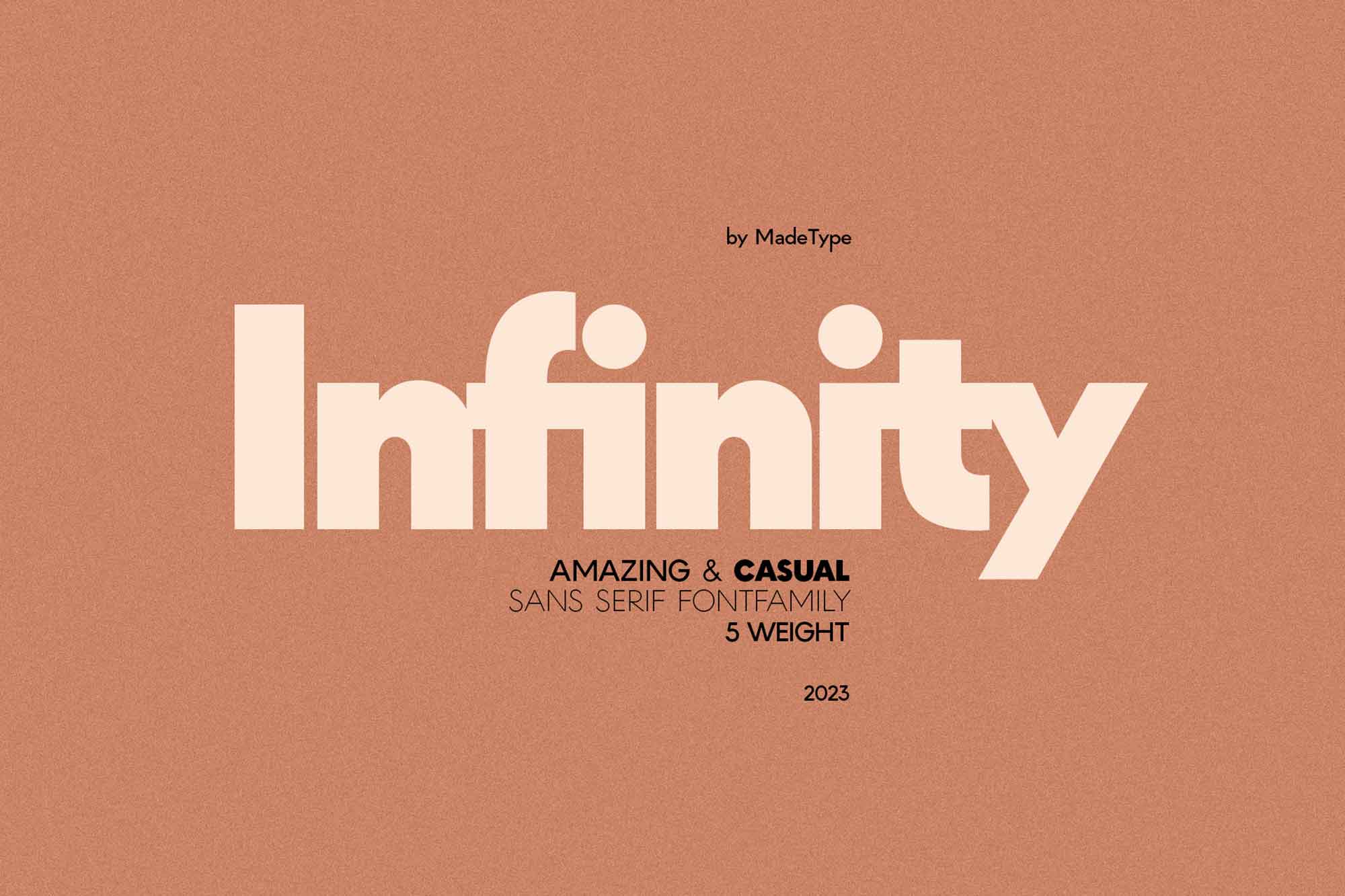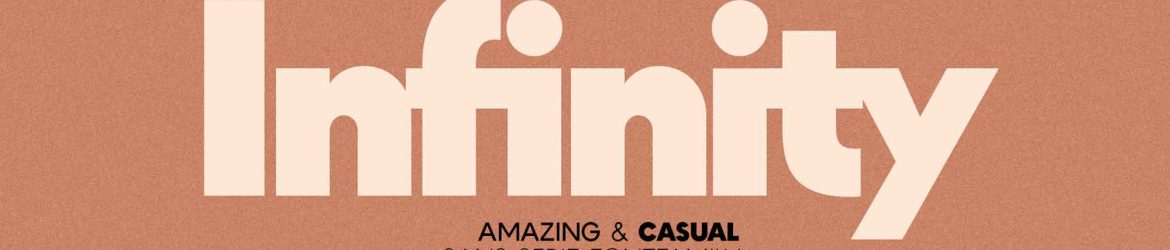
Made Infinity Font – Download Grátis
A Made Infinity é uma família de fontes sans-serif que compreende cinco pesos: fino, leve, regular e grosso. Suas linhas elegantes e elegantes fazem deste um recurso fonte perfeito para projetos que exigem uma mistura de simplicidade e versatilidade. O resultado é um design que é tanto amigável quanto versátil. A Made Infinity é uma ótima escolha para os designers gráficos que buscam uma fonte que seja elegante e versátil. Suas linhas delicadas e geométricas são perfeitas para aplicações em posters, capas de livros e revistas, posts de redes sociais, designs de sites, aplicativos móveis e banners. Sua simplicidade e modernidade fazem dele um recurso fonte inestimável, tanto para designers profissionais quanto para iniciantes. A Made Infinity é uma ótima adição à sua coleção de recursos fontes.